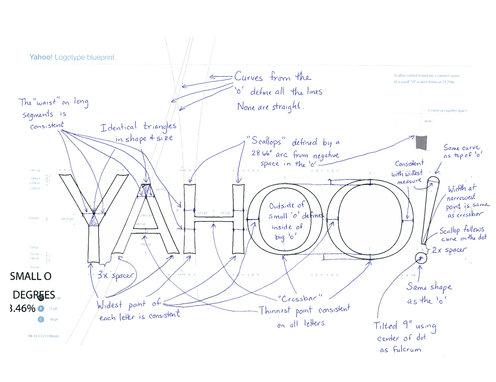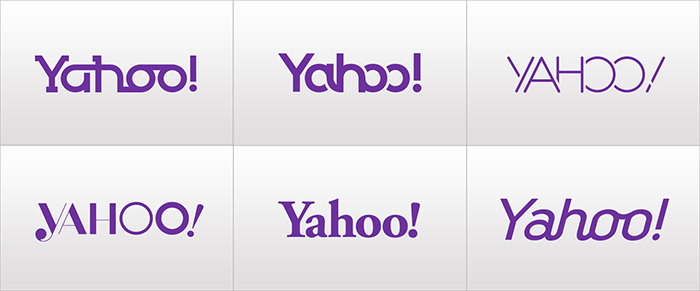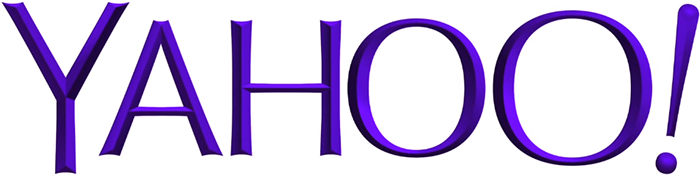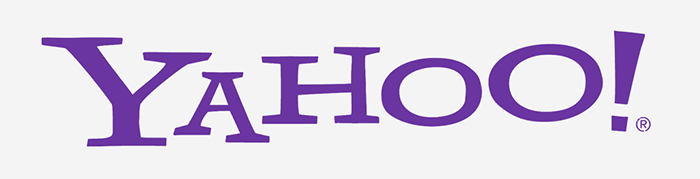
Nach 18 Jahren ändert Internet-Pionier Yahoo sein allseits bekanntes Logo. Die Präsentation kam nicht überraschend. In einer bislang sicher einzigartigen Aktion präsentierte man 30 Tage lang jeweils ein neue Logo. Große Begeisterung löste man damit jedoch nicht aus. Die Logo-Variationen wirkten einfach wie beliebige Spielereien mit Schriften – ohne jegliches Konzept.
Auch das am 30. Tag präsentierte – und damit endgültige – neue Logo reiht sich hier nahtlos ein.
Das bisherige Logo
Das neue Logo
Chefin Marissa Mayer berichtet in Ihrem Blog freimütig über die Entwicklung des neuen Logos. Sie sei ein großer Fan von Marken, Design und insbesondere Adobe Illustrator. An einem Wochenende hätte sie sich mit Bob Stohrer, Marc DeBartolomeis und Russ Khaydarov zusammengesetzt und verschiedene Ideen durchgespielt. »Whimsical, yet sophisticated« sollte es sein. Etwas verrückt, aber doch anspruchsvoll und durchdacht.
Als optische Würze kam noch ein Meißel-Effekt in die positive und negative Version des Logos hinzu.